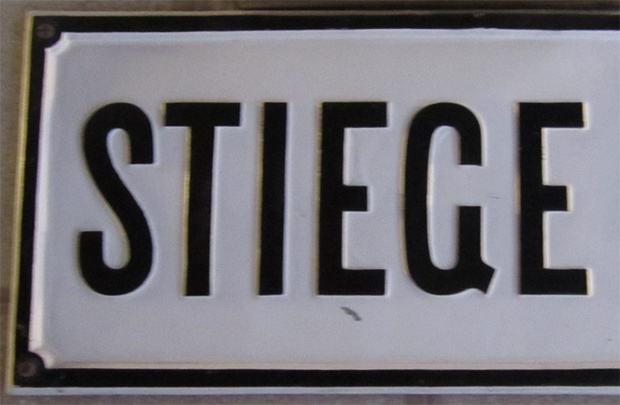
Schrift gesucht: Versalien auf Schild im Wiener Rathaus
bin auf der Suche nach der Schrift auf angehängtem Bild. Diese Tafel befindet sich im Wiener Rathaus bei den Treppen. Im Rathaus selbst weiß leider niemand darüber bescheid :-(
Würde mich sehr freuen, wenn mir jemand einen Tipp geben könnte, was das für eine Schrift ist und ganz großartig wäre zu erfahren, wo man sie kaufen kann!
Das ist bestimmt ein Eigenbau von dem Schilderhersteller, oder!?
... Beim ›Q‹ hat er ein Stück raus gefeilt und es als ›G‹ verwendet :lol:
obwohl das G schon irgendwie einen Witz hat, finde ich.
Vl gibt es eine Schrift, die derjenigen auf dem Schild nahe kommt…